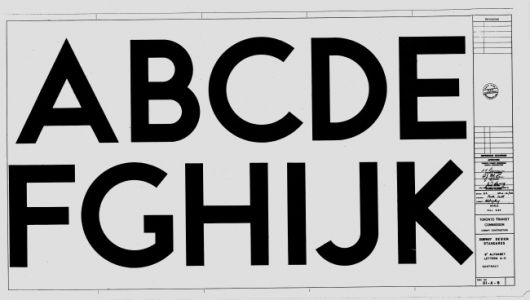
Toronto Subway Font
:arrow: Da spricht auch Gerald Fleuss über The legacy of Edward Johnston, von dem bekanntlich die Typographie der Londoner U-Bahn stammt.